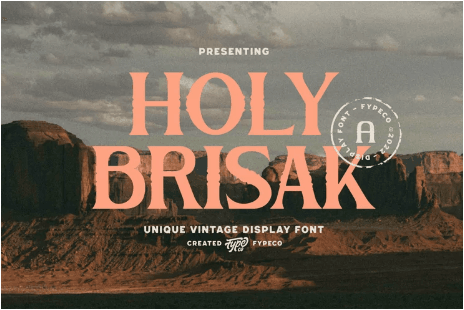
Шрифт Holy Brisak
Holy Brisak Font
Holy Brisak — это винтажный шрифт с засечками и уникальными деталями. Этот шрифт прекрасно подходит для логотипов, дизайнов, этикеток, одежды или всего, что вы хотите, с оттенком классического вестерна. Holy Brisak также поставляется с многоязычной поддержкой.